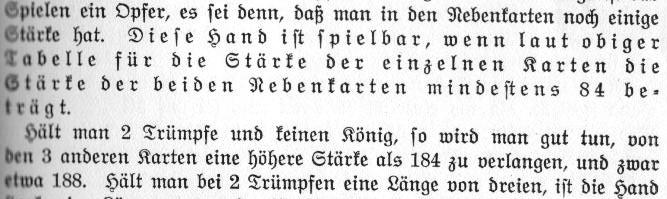
Sperrung in historischen Texten, Spezialfall Zahlen
Eine Frage an die Historikerfraktion unter euch:
Ich habe hier Zeitungsartikel aus der Revolutionszeit 1848/49, erschienen in einer preußischen Zeitung, gesetzt in Fraktur. Meine Frage bezieht sich auf Hervorhebungen im Text durch Sperrung. Wie ging man damals mit Zahlen um? Es geht konkret um das Datum 12. April 1822: Der Monat ist gesperrt, die Zahlen nicht (der Punkt schon gar nicht, an diese Konvention meine ich mich zu erinnern). Aus dem Kontext ist klar, dass es darauf ankommt zu betonen, dass es sich bei dem Gesetz, das an diesem Tag Geltung erlangte, um ein ALTES Gesetz handelt, es ist also inhaltlich auszuschließen, dass wirklich nur der Monat hervorgehoben werden sollte. Wenn ich andere Stellen hinzunehme, an denen Zahlen im Zusammenhang mit Sperrungen auftauchen, ergibt sich für mich als typografische Regel der Zeit, dass Zahlen grundsätzlich nicht gesperrt wurden. Ist das so?
Ich frage deshalb, weil wir uns entschieden haben, in der Wiedergabe der alten Texte Sperrungen durch Kursivsetzung aufzulösen. Das führt natürlich im angesprochenen Fall zu Schwierigkeiten, weil "12. April 1822" absurd ist. Meine Lösung besteht im Moment darin, die Zahlen selbstverständlich auch kursiv zu setzen und im Kritischen Bericht allgemein darauf hinzuweisen, dass es Stellen gibt, die im Original nach historischer Konvention nicht gesperrt wurden, aber dennoch sinngemäß Teil der Hervorhebung waren und deshalb auch kursiv gesetzt werden. Das setzt aber voraus, dass meine Annahme bezüglich der Konvention stimmt ...
Und eine Anschlussfrage: Ich nehme an, dass die Regel, nicht zu sperren, auch für die Zählung von Herrschern galt, dass man also in "Friedrich Wilhelm IV." die IV nie gesperrt hätte. Korrekt?
Zumindest hierfür habe ich eine Ausnahme gefunden, da ich hier ein Buch habe, in welchem eine gesprerrte römische Ziffer auftaucht, es stammt allerdings aus dem Jahre 1939 (s.u.) und ist daher evtl. eine Ausname. Allerdings ist es (für mich) recht schwierig, überhaupt Stellen zu finden, in denen es sinnvoll wäre, eine Zahl zu sperren.
EDIT: Außerdem habe ich noch ein Beispiel für gesperrte arabische Zahlen gefunden, aus dem Jahre 1929.
Zur Abb.: (1) (aus A. Funke: Bismark. der deutſche Menſch. Berlin 1939. S. 163.). Man vergleiche die (gesperrte) römische III in der ersten Zeile mit der (nicht gesperrten) römischen VIII in der 3. Zeile.
(2) (aus E. Lasker: Das verſtändige Kartenspiel. Berlin 1929. S. 49.) Man vergleiche die gesperrte 84 in der vierten Zeile mit der ungesperrten 184 in der siebten Zeile
Du könntest doch stattdessen ganz konkret werden und darauf hinweisen, dass du Zahlen, die nicht gesperrt, aber sinngemäß Teil von Hervorhebungen waren, kursiv gesetzt hast. Angenommen die Konvention, arabische Ziffern nicht zu sperren, gab oder gibt es im Fraktursatz, so könntest du trotzdem nicht vollkommen ausschließen, dass der Autor einige der nicht gesperrten Zahlen, die an gesperrte Textstellen grenzen, aus anderen Gründen nicht gesperrt hat. D. h. du kannst eigentlich nicht mit der Konvention argumentieren. Dass aus a immer b folgt, bedeutet nicht, dass b immer aus a gefolgt sein muss.
Edit: Wenn du den Text komplett in Antiqua setzt, ist das nicht selbst eine Form der Interpretation, u. z. eine Interpretation, die stärker ist als die sorgfältige Interpretation der Zahlen als Teil von Hervorhebungen?
Kann man natürlich machen, ist aber bei dutzenden Fällen nicht sehr praktikabel und wirkt vor allem unnötig pedantisch (wenn eine schlichte historische Konvention dahintersteckt) und lenkt von den textkritischen Erläuterungen ab, die inhaltlich von größerem Belang sind.
Ja, kann man nicht ganz ausschließen, ist aber im Gesamtzusammenhang (und zumal in diesem konkreten Fall) sehr unwahrscheinlich.
Bei jeder Textedition gehen Aspekte des Originals verloren, und jede Änderung ist im weitesten Sinne eine Interpretation, klar. Frakturtexte in Antiqua wiederzugeben halte ich dabei allerdings für die unproblematischste Anpassung des historischen Originals. Schwerer wiegt schon die Frage der Auszeichnung: Sperrung in Frakturtexten wirkt (jedenfalls auf mich) in der Tat anders als Kursivsetzung in Antiquatexten; die kursiven Stellen springen mich geradezu an beim Lesen, die gesperrten Passagen in Fraktur tun das nicht in gleicher Weise.
Zumindest das zweite Beispiel kommt aus einem Buch, von dem ich glaube, dass der Setzer nicht der Allerbeste war (Falls gewünscht, kann ich diesbezüglich Passagen zur besseren Einschätzung veröffentlichen, aber die haben dann nichts mehr mit dem hiesigen Thema).  Von daher kann es durchaus sein, dass konventionsgemäß Zahlen eigentlich nicht gesperrt werden, nur der Setzer diese Konvention nicht gekannt oder bewusst ignoriert hat. Um diese Frage zu klären, wäre es schön, entweder mehr Gegenbeispiele oder gar einen Literaturnachweis zur Sperrung von Zahlen zu haben.